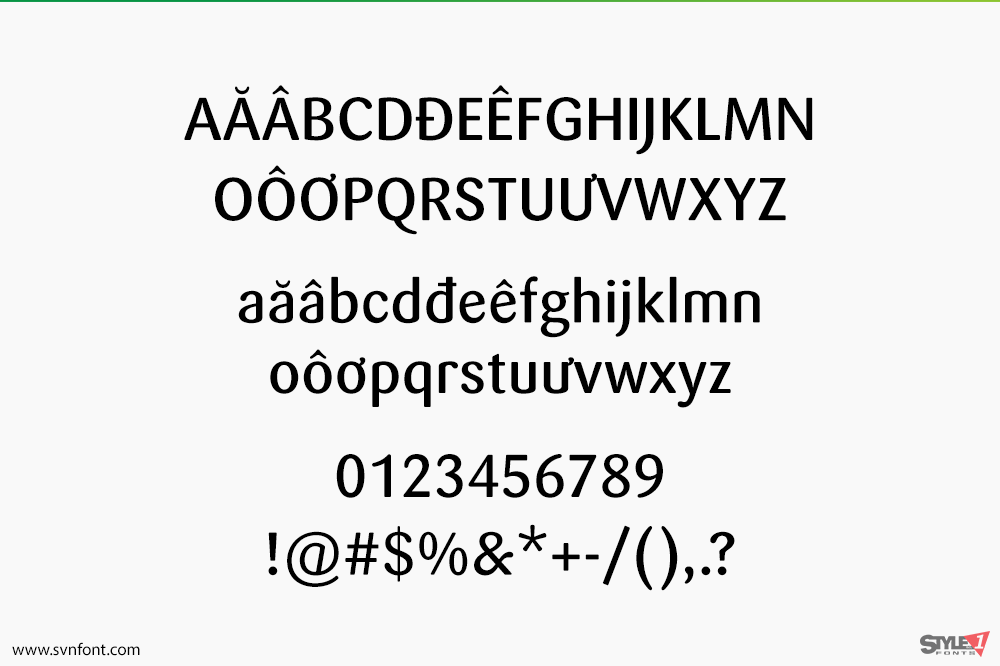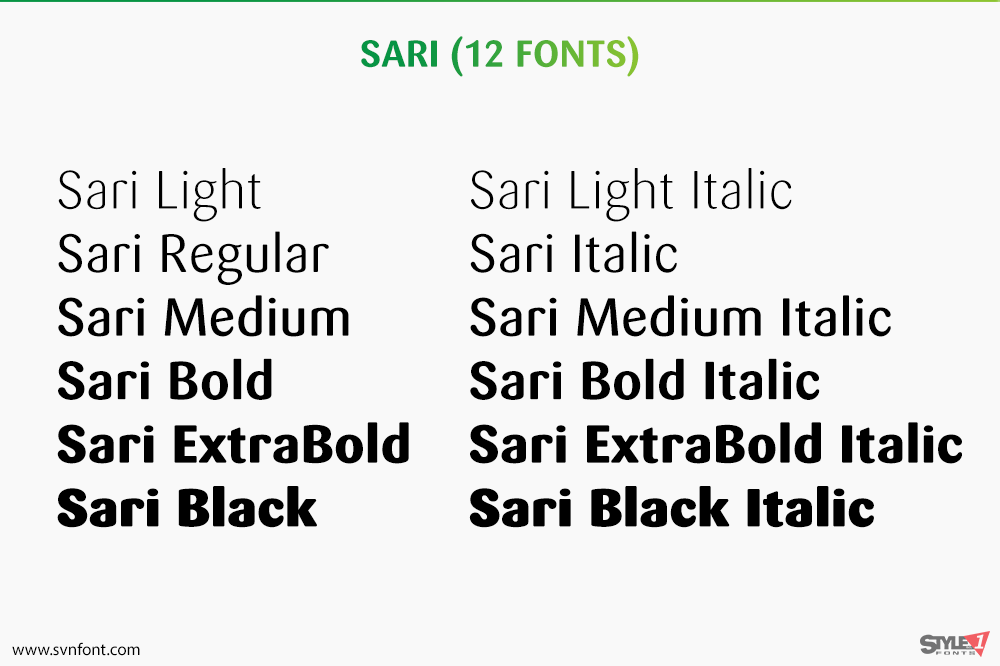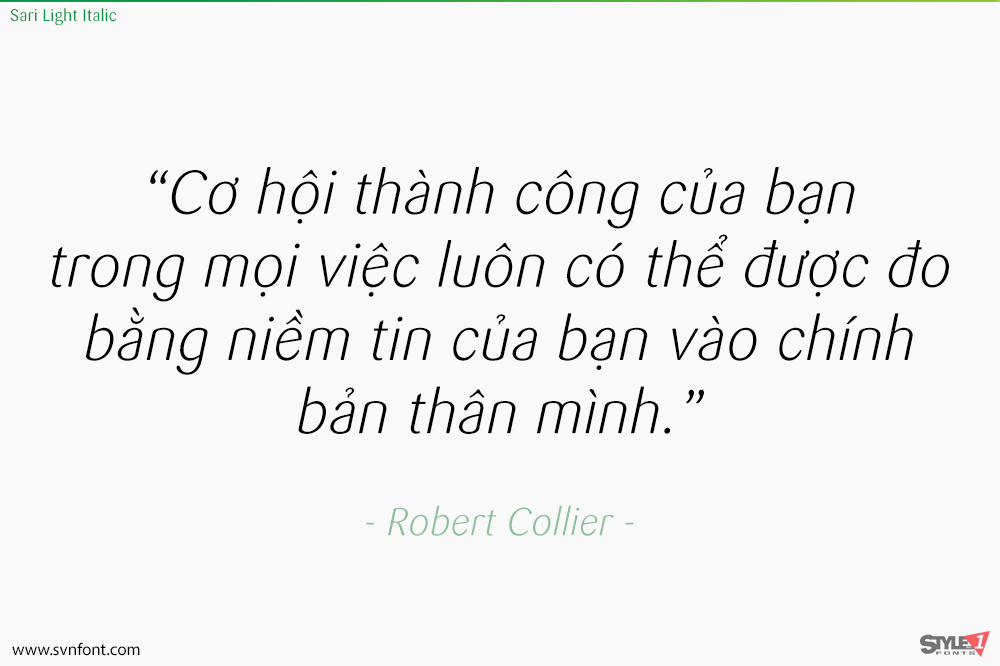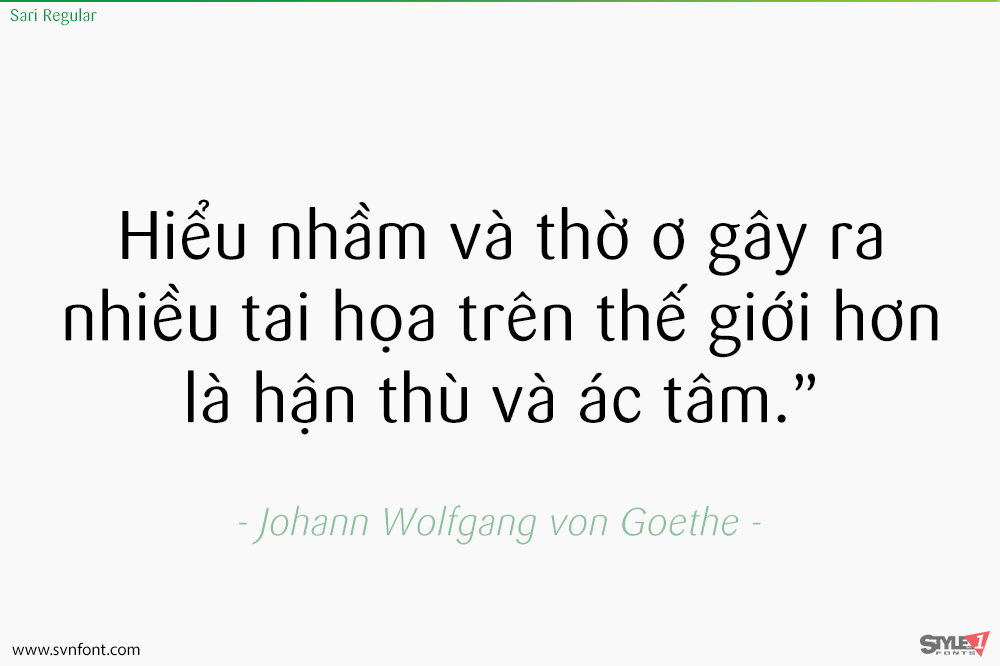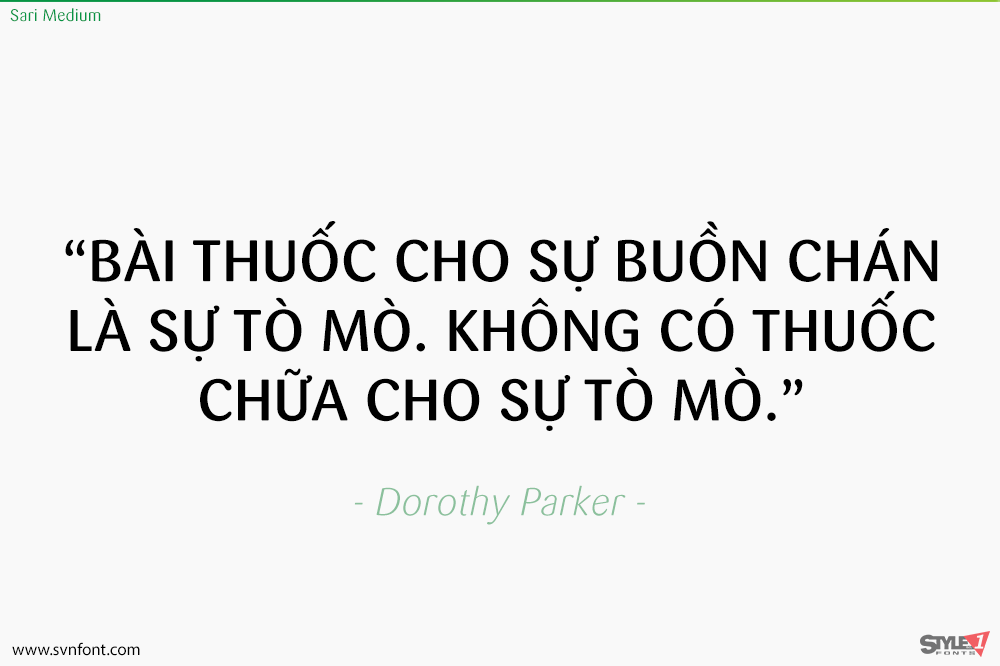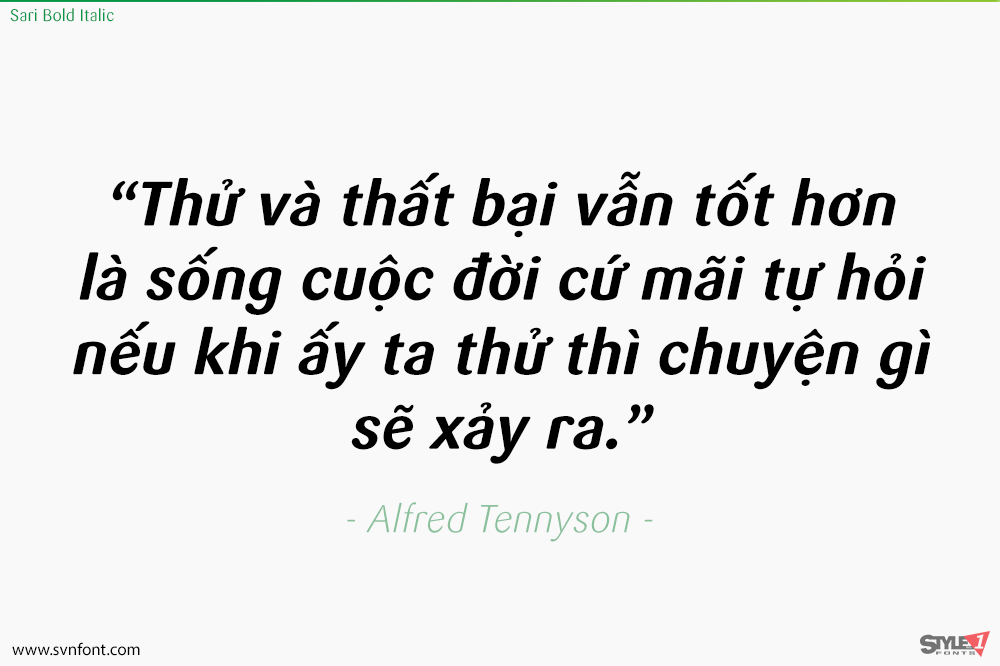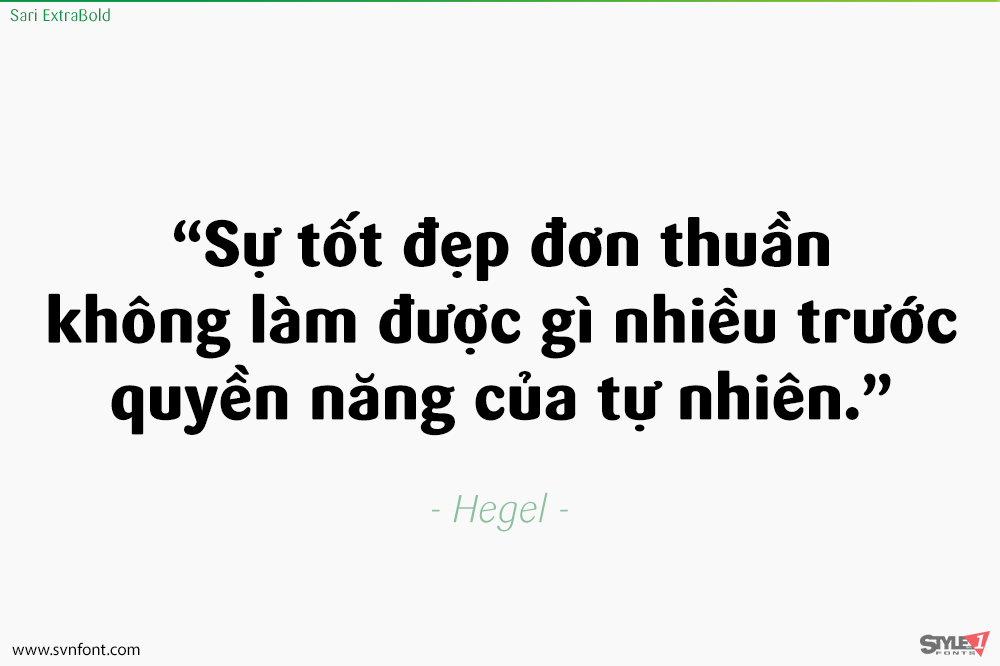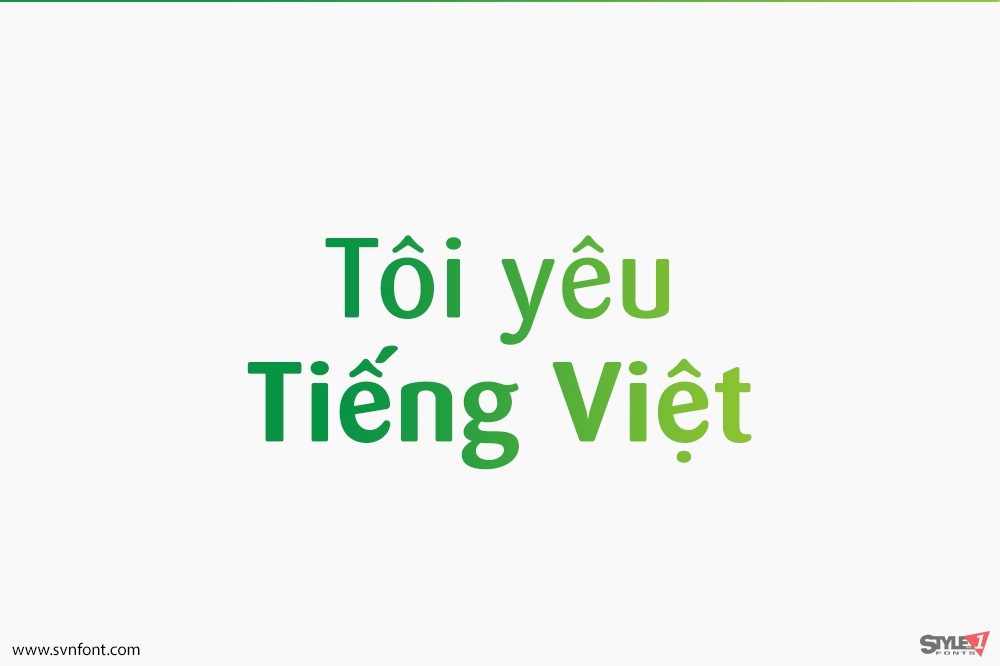
Nhà thiết kế kiểu chữ người Đức Hans Reichel đã tạo ra phông chữ sans FF Sari này vào năm 1999. Họ phông chữ này có 14 styles, từ Light đến Black (bao gồm cả kiểu in nghiêng), và lý tưởng cho các lĩnh vực như quảng cáo và bao bì, các dịp lễ hội, biên tập và xuất bản, logo, xây dựng thương hiệu và các ngành công nghiệp sáng tạo, áp phích và bảng quảng cáo lớn, cũng như thiết kế web và màn hình. Nó đi kèm với một bộ tùy chọn chữ số hoàn chỉnh – chữ số kiểu cũ (oldstyle) và chữ số thẳng hàng (lining figures), mỗi loại đều có chiều rộng dạng bảng (tabular) và tỷ lệ (proportional).
Nhà thiết kế: Hans Reichel